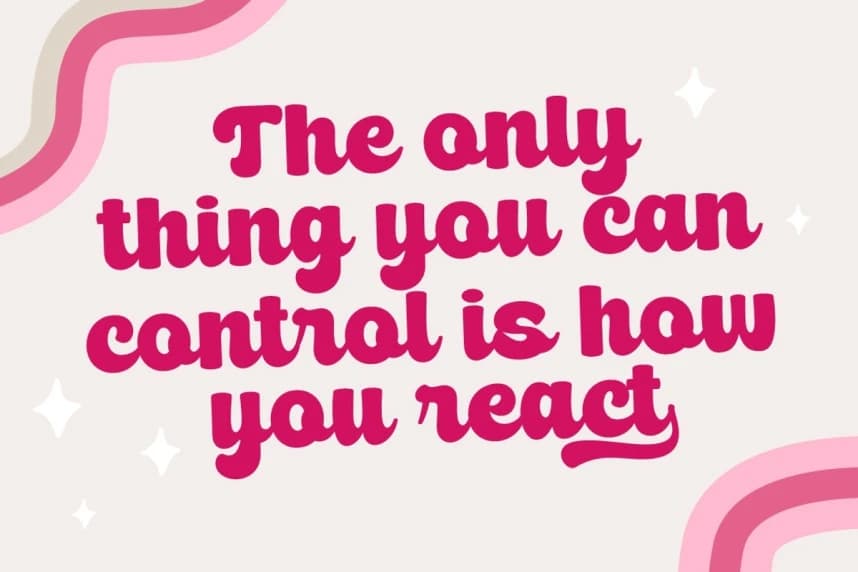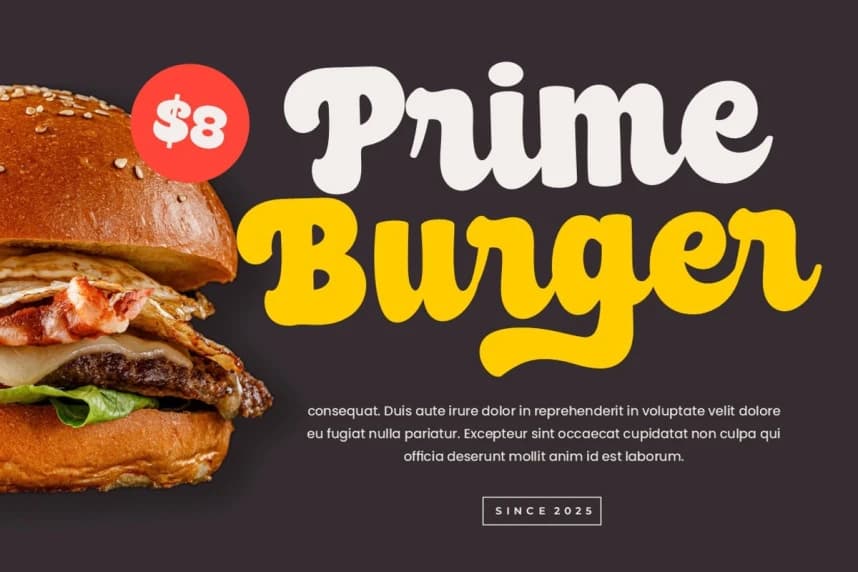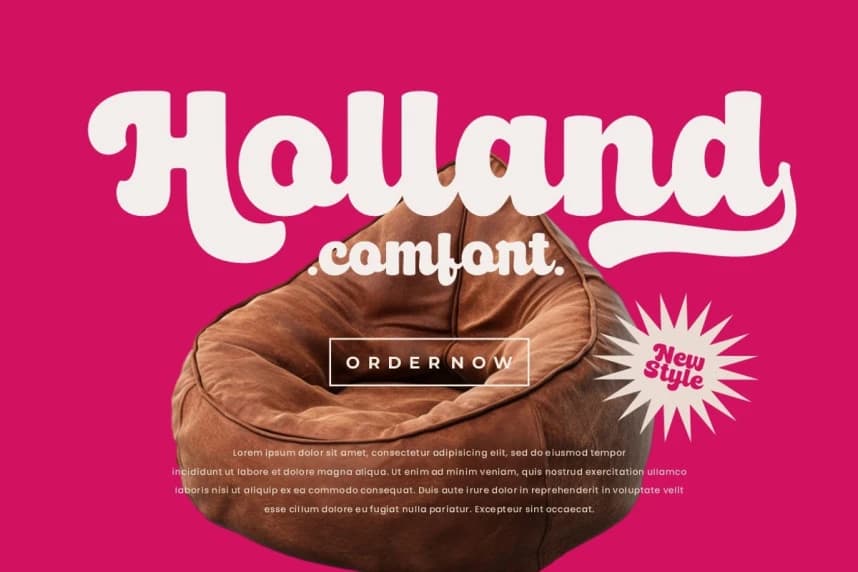
Milky Bun Font
Milky Bun Font, yuvarlatılmış dokunuşa sahip cesur bir retro yazı tipi stilidir. Büyük harflerden küçük harflere, rakamlardan noktalama işaretlerine kadar tüm karakter setine sahip ve çok dilli desteğe sahiptir; bu font herhangi bir projede kullanıma hazırdır.
Milky Bun Font, köşeleri yuvarlatılmış dokunuşa sahip kalın bir retro yazı tipi stilidir. Büyük harflerden küçük harflere, rakamlardan noktalama işaretlerine kadar tüm eksiksiz karakter seti ile çok dilli desteğe sahiptir; bu font herhangi bir projede kullanıma hazırdır.